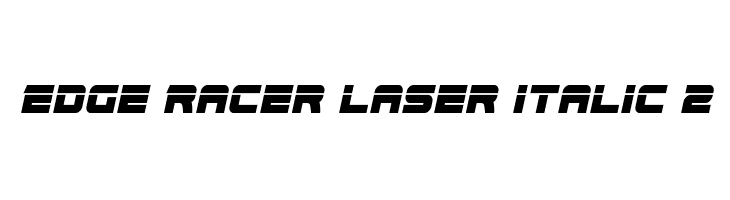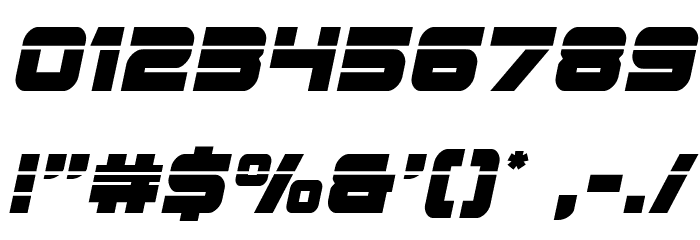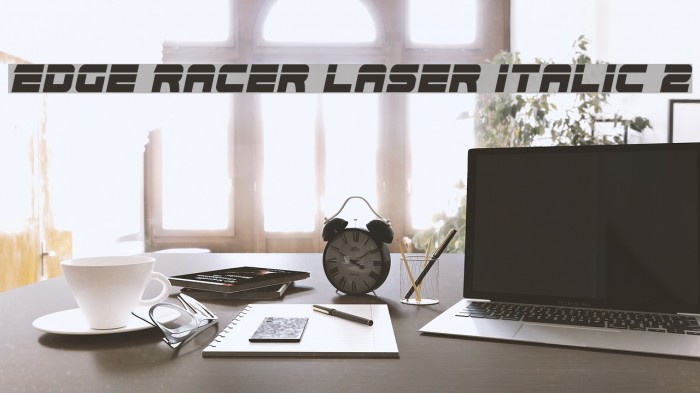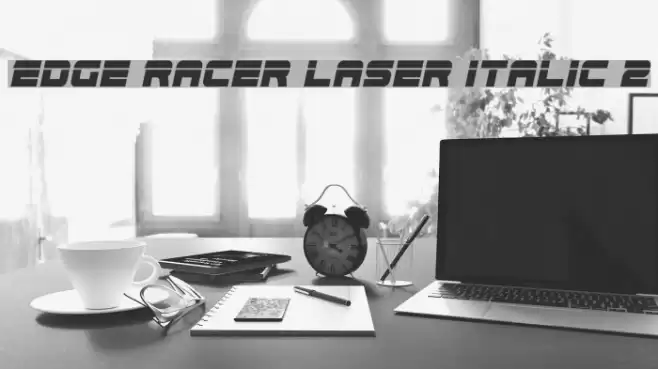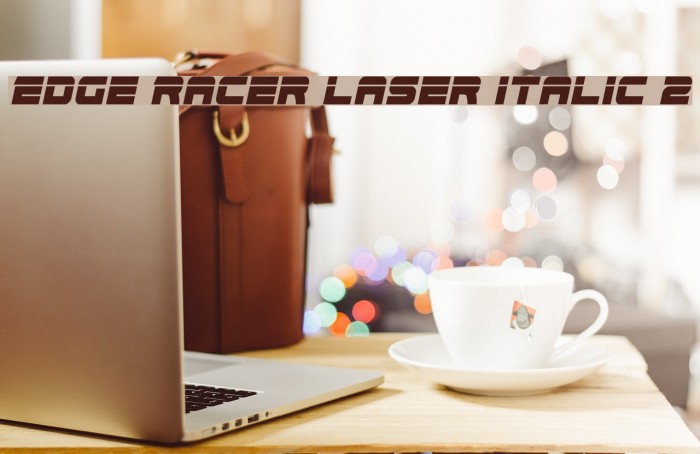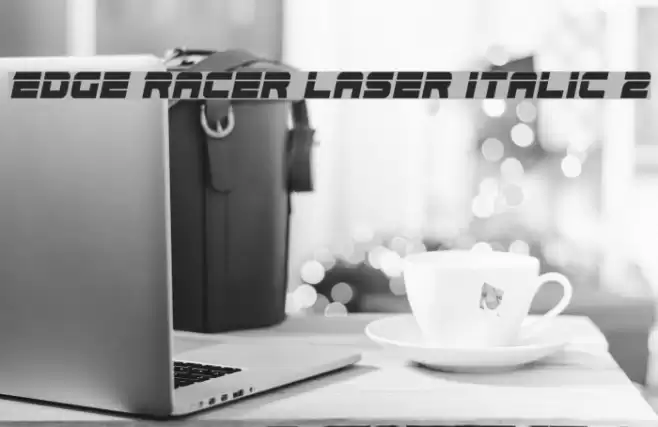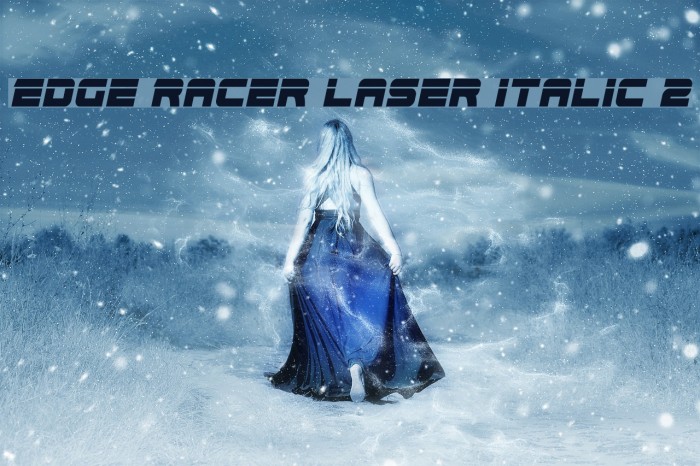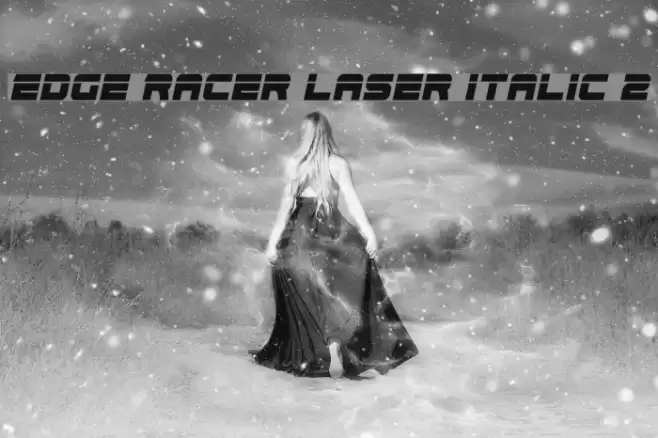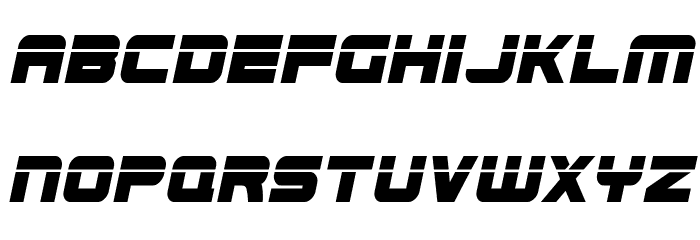
Edge Racer Laser Italic 2 Font
| おすすめプロジェクト | Ideal for automotive branding, tech product advertisements, and video game titles. |
Edge Racer Laser Italic 2